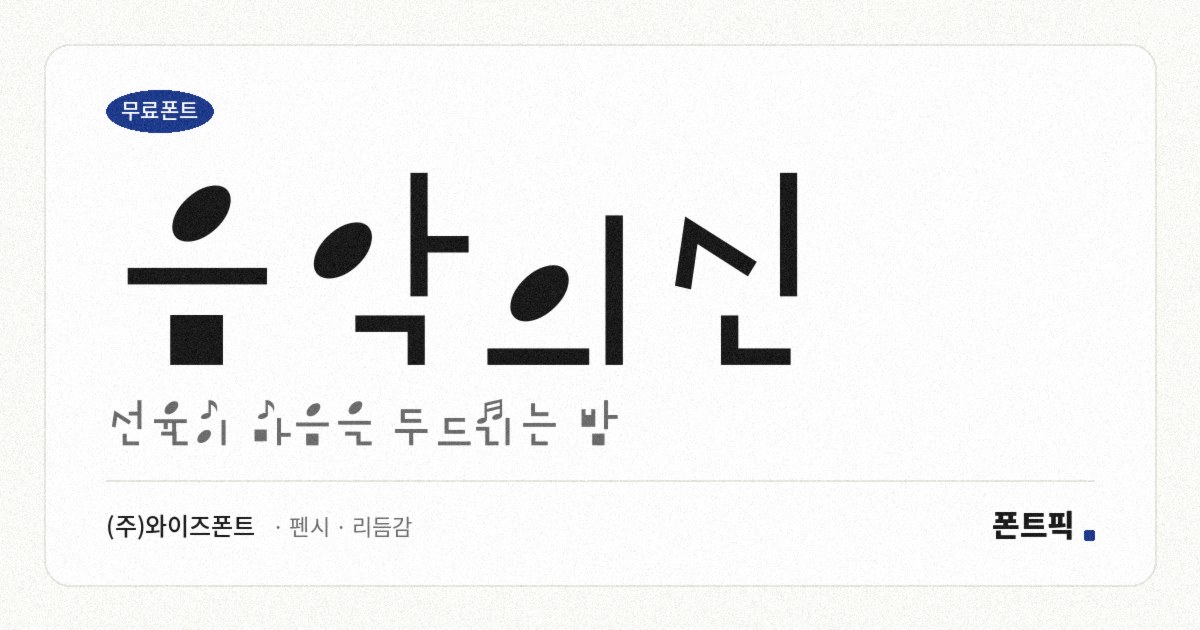
음악의신
TDTDGodofMusic
- 분류펜시 · 리듬감
획을 직선으로 각지게 꺾고 그 사이에 음표를 끼워 넣은 서체입니다. 가와 나, 다, 사 같은 글자마다 음표가 붙어 있고 한글뿐 아니라 영문과 숫자까지 같은 방식으로 변형돼 있습니다.
파일에서 재어 보면 낱자가 폭보다 높이가 커서 세로로 선 인상이고, 받침이 붙어도 높이가 거의 변하지 않는 네모틀입니다. 장식이 많은 서체치고는 구조가 정돈된 편입니다.
다만 읽는 부담은 같은 회사 서체 가운데 가장 큽니다. 음표가 획 사이에 끼어 있어 글자와 장식의 경계가 흐려지기 때문입니다. 공연 포스터나 플레이리스트 표지의 제목 한 단어처럼, 읽기보다 보는 자리에 두는 것이 맞습니다. 현대 한글 11,172자를 모두 담았고 굵기는 하나입니다.